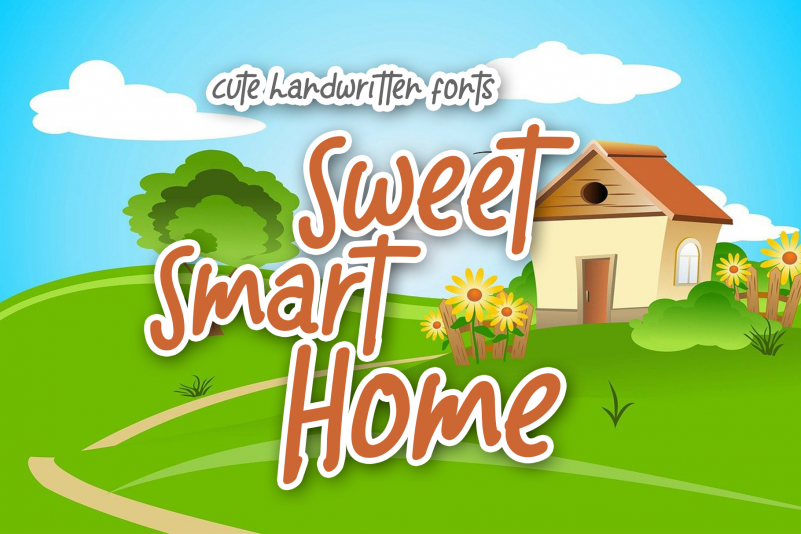
Sweet Smart Home Display Font – Download Grátis
A fonte “Sweet Smart Home Display Font” é uma escolha perfeita para designers que desejam criar ambientes agradáveis e contemporâneos ao mesmo tempo, seja em letras de apresentação ou em materiais de escritório. Sujeitosa e moderna, esta fonte mantém suas influências tipográficas clássicas enquanto parece fresca e atual. Seu estilo versátil e seu design sofisticado fazem dela uma escolha ideal para quem busca um tom elegante para seus projetos. Ideal tanto para letras de cartão-postal ou para nomes, quanto para papel de escrita ou materiais decorativos, a fonte “Sweet Smart Home Display Font” é uma excelente opção para designers que desejam dar um toque especial aos elementos visuais de seu projeto.